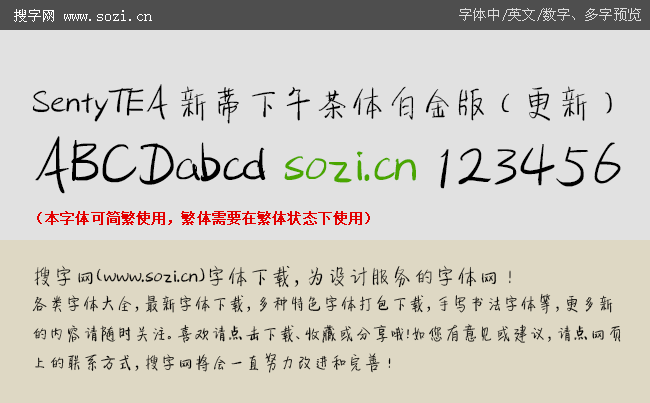
新蒂下午茶體白金版(更新)
搜字網(wǎng)給大家提供一款書法風(fēng)格的字體新蒂下午茶字體下載。新蒂下午茶字體是一款手寫風(fēng)格的中文簡體字體,非常有手寫感,廣泛應(yīng)用于簽名、藝術(shù)設(shè)計(jì)、創(chuàng)意廣告等行業(yè),喜歡的用戶可下載收藏。